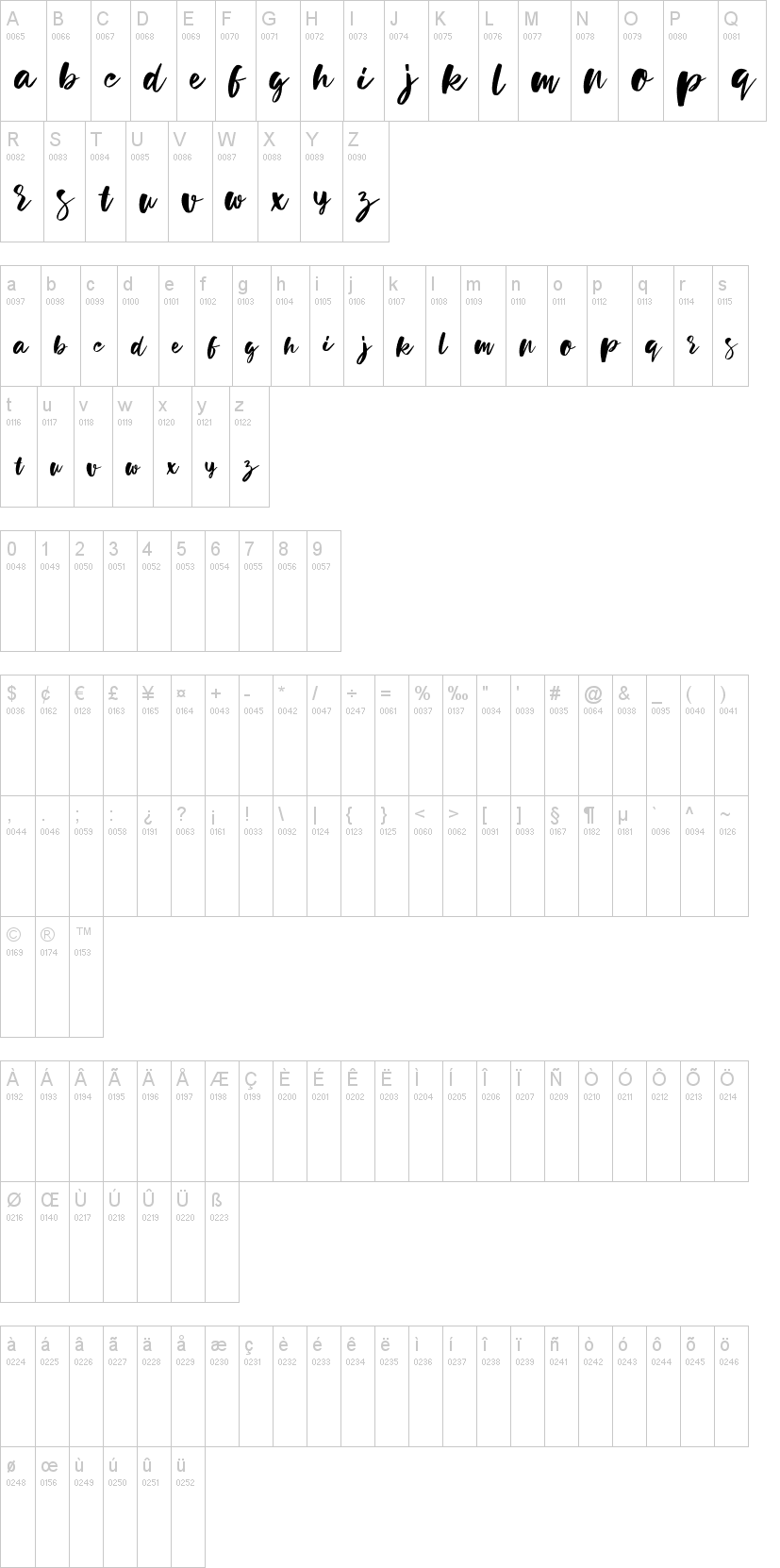
Holiday Sun
Holiday Sun字体是一款由Fontscafe设计的手写字体,它具有温暖的夏日气息,充满活力和欢乐的气氛。它的笔画柔和,充满了温暖和活力,是一款非常适合假日和庆典的字体。它可以用于节日卡片、海报、T恤、海报和其他设计。它的设计风格简单,易于阅读,可以轻松地传达出欢乐的气氛和活力。
Holiday Sun是一款非常不错的手写艺术字体,具有很好的视觉感,适合于文化类的宣传设计、商业类品牌的广告和产品包装设计以及个性化文字排版等较多场景。
Holiday Sun字符映射图